除了包管理器,你还可以从思源字体的官方GitHub仓库下载。思源黑体、思源宋体由Adobe和Google联合开发,支持简繁日韩,是当今Linux桌面最专业的中文字体。访问release页面下载OTF或TTF文件,解压后放到~/.local/share/fonts目录下即可供当前用户使用。
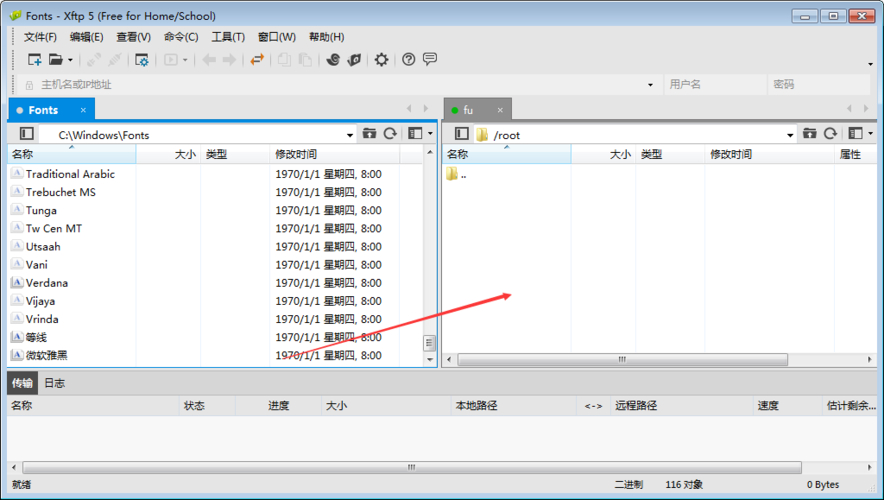
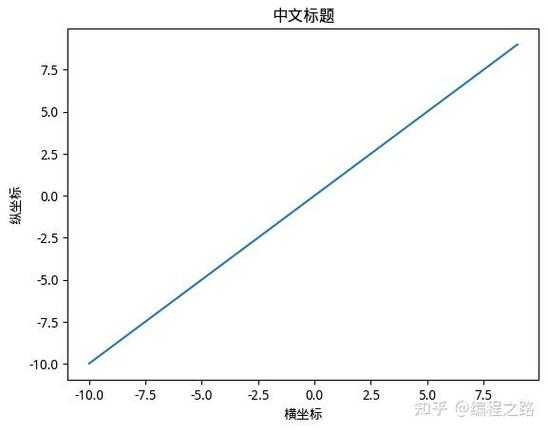
Linux中文显示乱码怎么解决
系统显示中文变成小方块或问号,根本原因往往是缺少中文字体或locale配置错误。优先检查是否安装了任意一种中文字体,执行“fc-list :lang=zh”如果没有输出,说明没有中文字体,请参考上面的下载安装方法添加文泉驿或思源字体。解决字体缺失后,绝大多数乱码也就消失了。
如果已有字体但某些软件仍然乱码,那么问题出在locale环境变量。运行“locale”命令查看LANG和LC_CTYPE的值linux 内核,它们应该包含zh_CN.UTF-8。若不是,编辑~/.bashrc或/etc/locale.conf北京linux培训,添加“export LANG=zh_CN.UTF-8”,然后重新登录。另外,老旧的GB18030编码文档建议用iconv转换为UTF-8再打开。
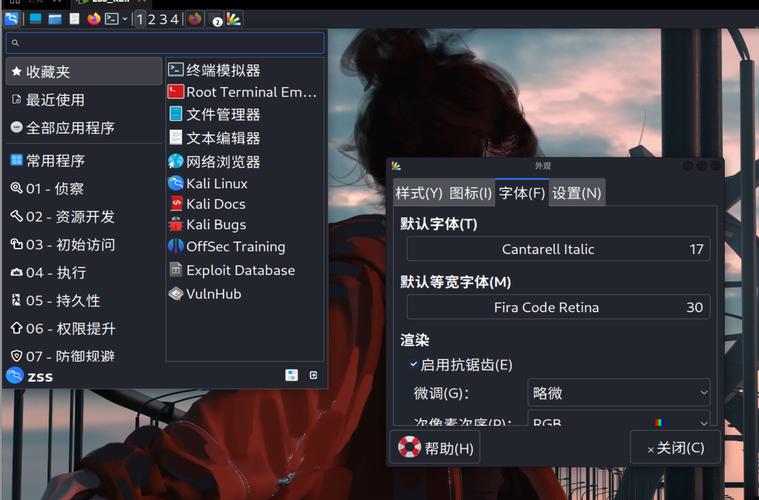
哪些中文字体最适合Linux桌面
对于日常办公和网页浏览,推荐优先安装文泉驿微米黑。它采用矢量字体技术,在低分辨率屏幕上依然清晰锐利,不会出现笔画模糊的问题。而且文泉驿是开源字体,任何Linux发行版都可以免费使用,你不需要担心版权风险。
如果你追求印刷级的显示效果,思源黑体无疑是最佳选择。它的字形现代、字重丰富(从ExtraLight到Heavy共7种),适用于标题、正文、代码注释等各种场景。同时思源宋体适合阅读长篇文章,其衬线风格在PDF文档中表现出色。注意思源字体文件较大,下载时选择分卷压缩包或仅下载需要的字重。
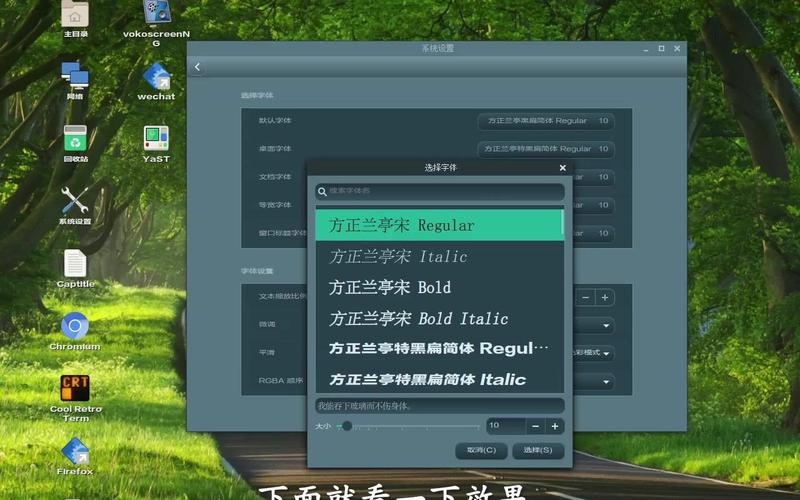
下载的付费中文字体能用在Linux吗
很多商业中文字体如方正、汉仪、华康等提供的是Windows格式的TTF文件,这些文件同样可以在Linux下安装使用。只要没有DRM加密,复制到字体目录并刷新缓存后,Linux桌面应用程序就能正常调用它们。但请务必遵守字体授权协议,个人使用通常无妨,商用则需要购买授权。
需要注意一个常见问题:部分商业字体的文件名或内部名称包含Windows专属的字符集标识linux 中文字体下载,可能导致fc-list识别异常。你可以在终端用“otfinfo”或“ttx”工具查看字体元数据,必要时用FontForge重新生成字体表。另外,某些付费字体的Hinting信息在Linux下渲染效果可能变差,建议配合Infinality或Freetype的微调选项使用。